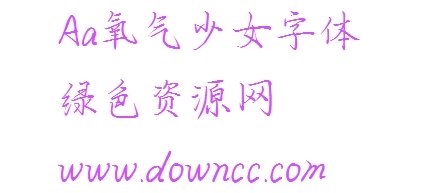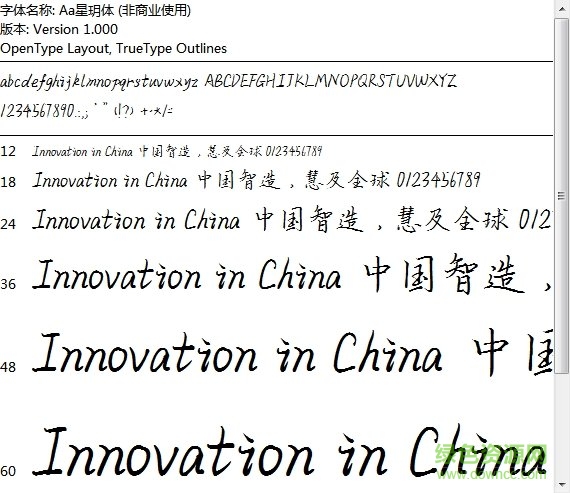
Aa氧氣少女字體
aa氧氣少女字體也叫aa星玥體,是一款書寫大方、運筆流暢的手寫字體,給人清晰娟秀的視覺效果,造型端正筆觸有力,喜歡就來綠色資源網(wǎng)試試吧!
氧氣少女體有著柔和的筆觸,用筆簡潔不拖沓,行筆流暢而不尖銳,給人十分舒適的藝術(shù)呈現(xiàn),可以廣泛運用在平面設(shè)計、海報設(shè)計、創(chuàng)意策劃等場合。
Aa氧氣少女字體即Aa星玥體!